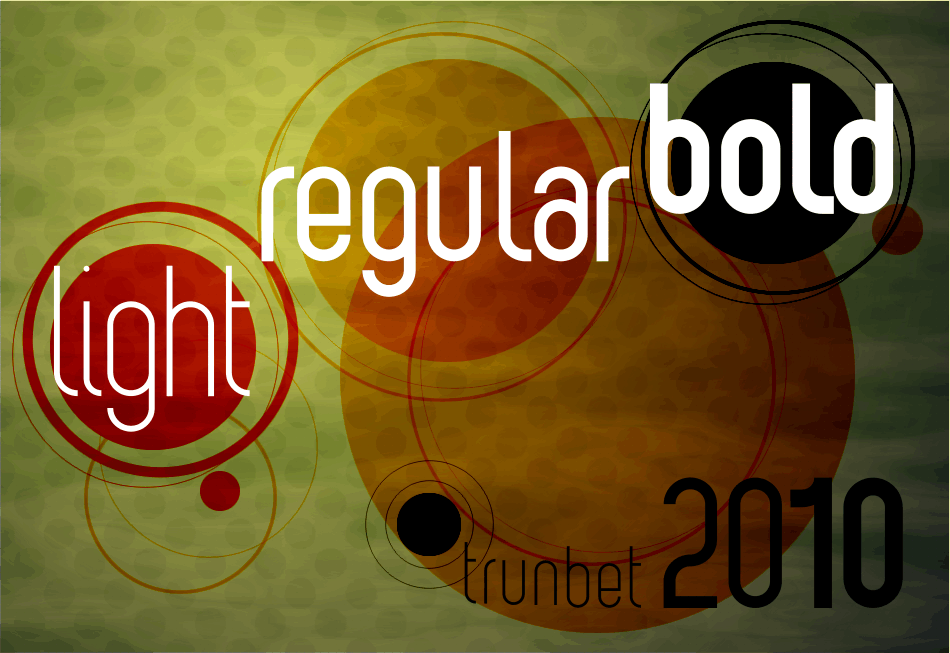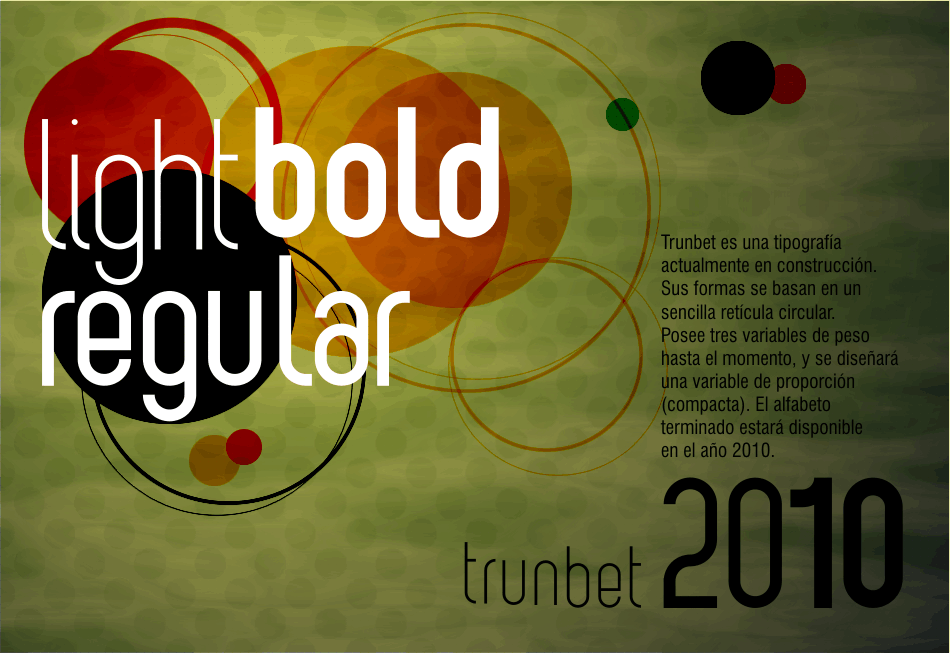
Tipografía Trescirc – Parte 2
Trunbet es una tipografía que actualmente estoy construyendo. Sus formas se basan en un sencilla retícula circular. Posee tres variables de peso hasta el momento (light, regular/medium, bold), y se diseñará una variable de proporción (compacta / expandida). El alfabeto terminado estará disponible en el 2010.